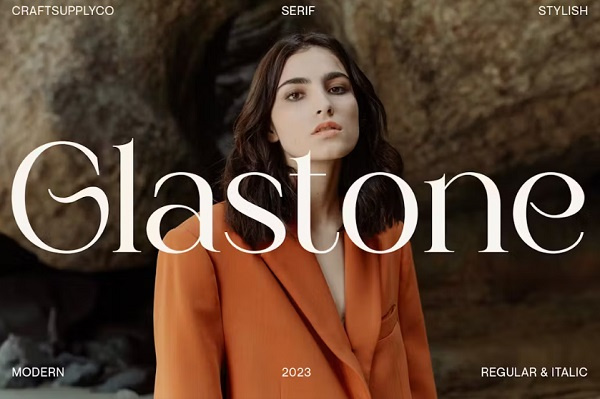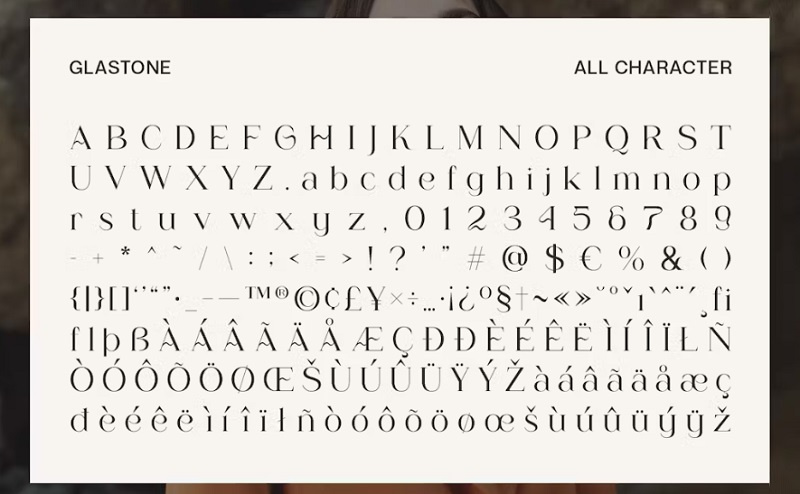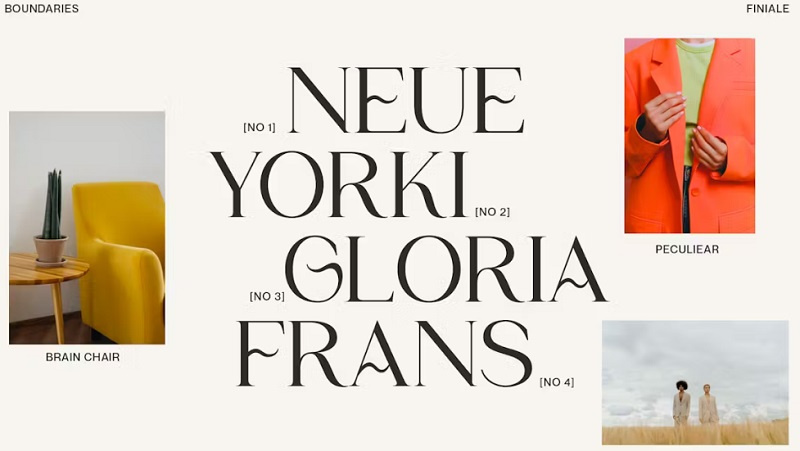
دانلود فونت انگلیسی Glastone
دانلود فونت انگلیسی Glastone از جی اف ایکس دانلود. یک فونت انگلیسی برای طراحی ظریف و مدرن می باشد. این فونت انگلیسی برای کارت تبریک، بسته بندی، هویت برند، پوستر یا هر هدفی ایده آل است تا پروژه طراحی شما را چشم نواز و مد روز جلوه دهد.
✅ نام فونت انگلیسی: Glastone
✅ شامل اعداد و علائم نگارشی